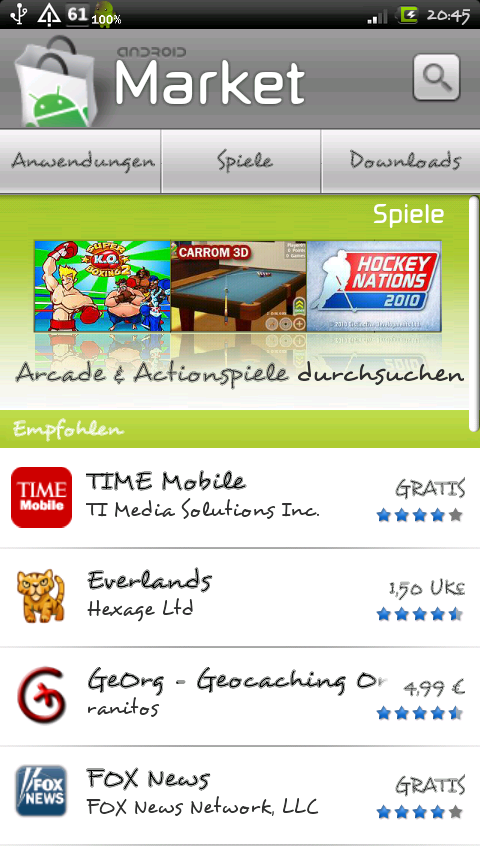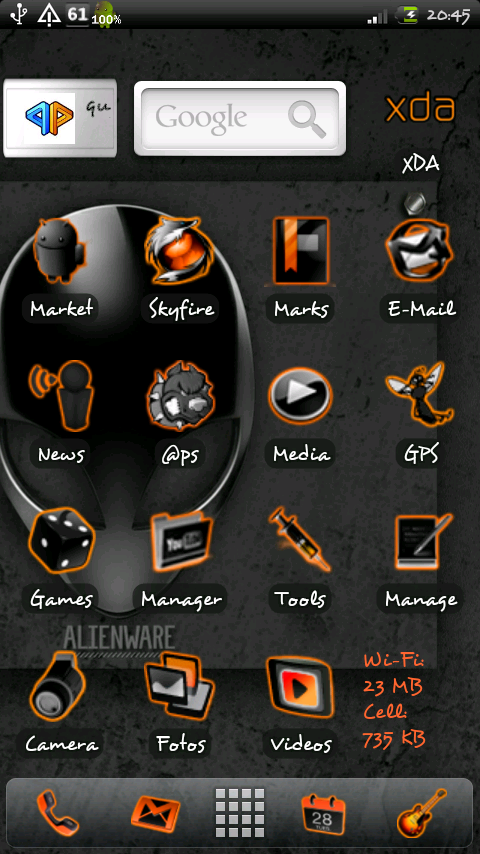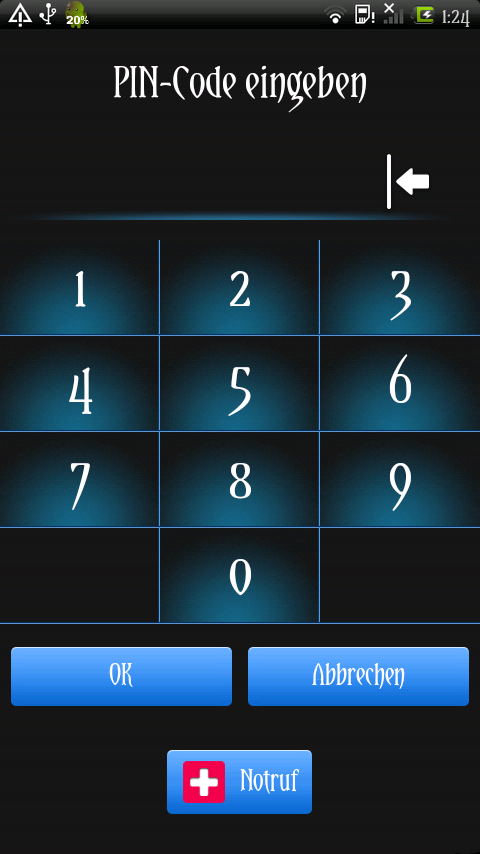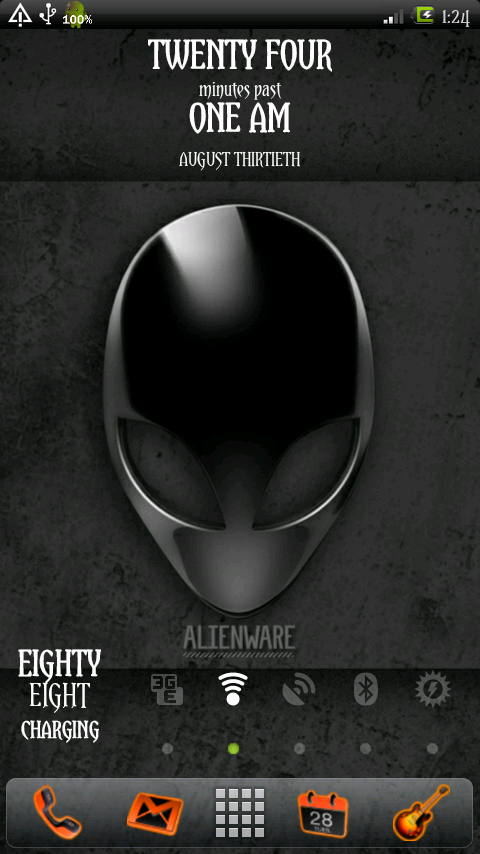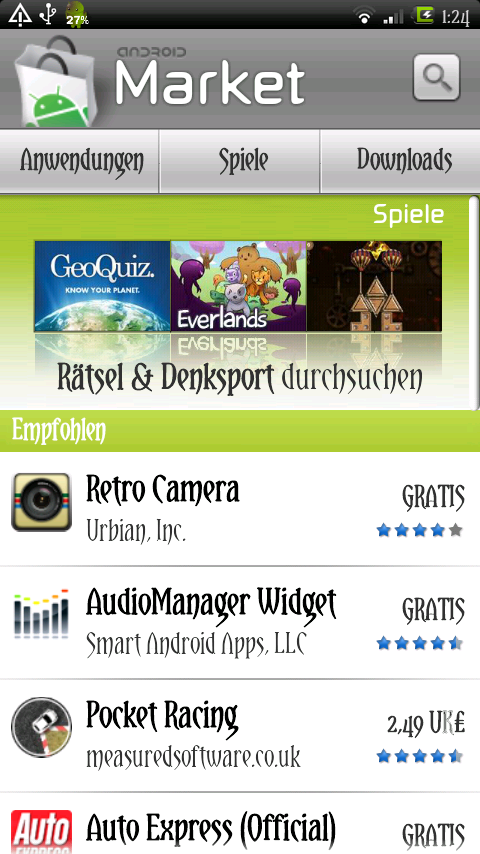
kann man eigentlich die schriftart des x10 ändern? damit meine ich nicht nur zum sms tippen oder so, sondern für ganze "betriebssystem" quasi. habe dazu nicht wiklich was über die su-fu gefunden. auch google gab nicht wirklich was her.
wer hat damit schon erfahrung?
Soweit ich weiss ist das nicht möglich...
Aber was soll das den bringen? An was für ne Schriftart hättest du den gedacht?
Naja, an was spezielles habe ich noch nicht gedacht, da ich ja nicht weis ob und vor allem wie das geht. aber wir feilen hier alle bis zum abwinken an unserem x10 rum, um es optisch aufzupeppeln, da gehört dann doch eigentlich auch eine besondere schriftart zu.
aber die frage ist eben wie aufwendig sowas ist und ob das überhaup so einfach machbar ist...
Doch, ist machbar. Hab schon viele gesehen dies gemacht haben, aber wie hab ich keine Ahnung... Im XDA-Forum gibts glaube ich nen Thread dazu. Such ihn gleich mal raus.
ja, genau sowas meine ich. zwar doof, das man wieder tausend sachen installieren muss vorher, aber ist scheinbar schonmal eine möglichkeit...
Bei mir funkts leider nicht aber habe es nur mit 1 Schriftart probiert.
Hallo Leute,
habe Gestern mal erfolgreich die Schrifftart geändert! Hat auch super geklappt.
Im XDA Forum hab ich auch jede menge verschiedene Arten gefunden.Man muß lediglich 2 Apps installieren (kostenlos und wirklich ganz klein), das stört eigendlich nicht. Das Problem ist nur das die meisten Schriftarten ziemlich klein sind und man sich schon fast anstrengen muß zum Lesen!Ich habe leider noch nix gefunden wie und ob man die Größe einstellen kann. Sieht aber richtig gut aus!!!
Wenn ich heut Mittag Zeit habe lade ich mal ein paar Screens mit unterschiedlichen Schriften hoch!
kann davon nur abraten! flashe gerade neu...
bin total begeistert^^
Wie hast du es denn gemacht?
Ich hab bestimmt schon 20 mal die Schrift geändert und noch nie Probleme gehabt.Ist halt nor schwierig die richtige zu finden wo die Schriftgröße und leserlichkeit stimmt!
@ quentin.
Das kann daran liegen, dass deine ausgewählte Schriftart nicht kompatibel mit dem X10 ist.
Wenn du dann neu bootest und die Schrift nicht kompatibel ist, bleibst du am SE Logo stecken und man kann neu flashen -.-.
nö der font wird unterstützt aber ich hatte alle neun fonts geändert^^
tja und jetzt meine schriftart auf sd/fonts
ich gehe ins typefresh und mach ein backup
jetzt ändere ich die ersten beiden fonts und drücke apply.
phone startet nicht neu und fonts werden auch nicht gewechselt.
ich rate weiter jedem davon ab.
unausgereifte geschichte und das type fresh hängt sich dauernd auf oder will nach der änderung nicht selbst rebooten.
und dadurch ist die ganze arbeit dann auch hinfällig.
wenn ihr euch den xda thread genau durchlest werdet ihr selbiges feststellen.
edit: also nach wie vor bekomme ich es ned hin den font zu ändern.
kp warum
hab es jetzt. mit fontflasher (free) einfach "mount system read/write" geclickt.
danach ab ins typefresh, font geändert und reboot...
trallala...
ich habe einen font gefunden den ich euch nicht vorenthalten will...
das besondere ist das er tatsächlich größer als der default font ist und das lesen dadurch wirklich ein wenig einfacher wird.
der font selbst bleibt allerdings geschmackssache wie so vieles...
den font findet ihr hier: http://www.fontsquirrel.com/fonts/li.../Display/50/50
er heisst yataghan...
auf selbiger seite findet ihr auch den font caviar dreams der sehr edel ist und ebenfalls größer als der default font.
beide laufen auf dem x10 problemlos.
hier noch screens vom yataghan. ganz schön groß oder?
kann man gut mit meinem letzten post im thread vergleichen.
Leider klappt es bei mir nicht.
Habe ich mir schon gedacht und auch so gemacht.
Leider ohne erfolg.
Gibt es eine ander möglichkeit die ein bischen einfacher ist die Schrifart zu ändern?